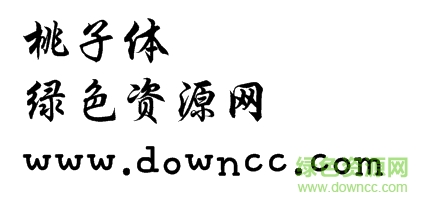
桃子體ttf
桃子體ttf是一款造型活潑清秀的pop字體,字跡連貫清雅,界面鋼筆書(shū)法和毛筆書(shū)法指尖,更顯娟秀端莊之美,喜歡的朋友不妨來(lái)綠色資源網(wǎng)體驗(yàn)吧!
桃子體字體介紹
桃子體充滿了水果的靈氣與活潑,自己上比較連貫,中英文書(shū)寫(xiě)都很有特色,中文偏向于宋體,有著飄揚(yáng)大氣之感,英文跳脫,更顯隨意閑適之味,可廣泛運(yùn)用于排版設(shè)計(jì)、平面設(shè)計(jì)、海報(bào)設(shè)計(jì)等領(lǐng)域!
桃子體